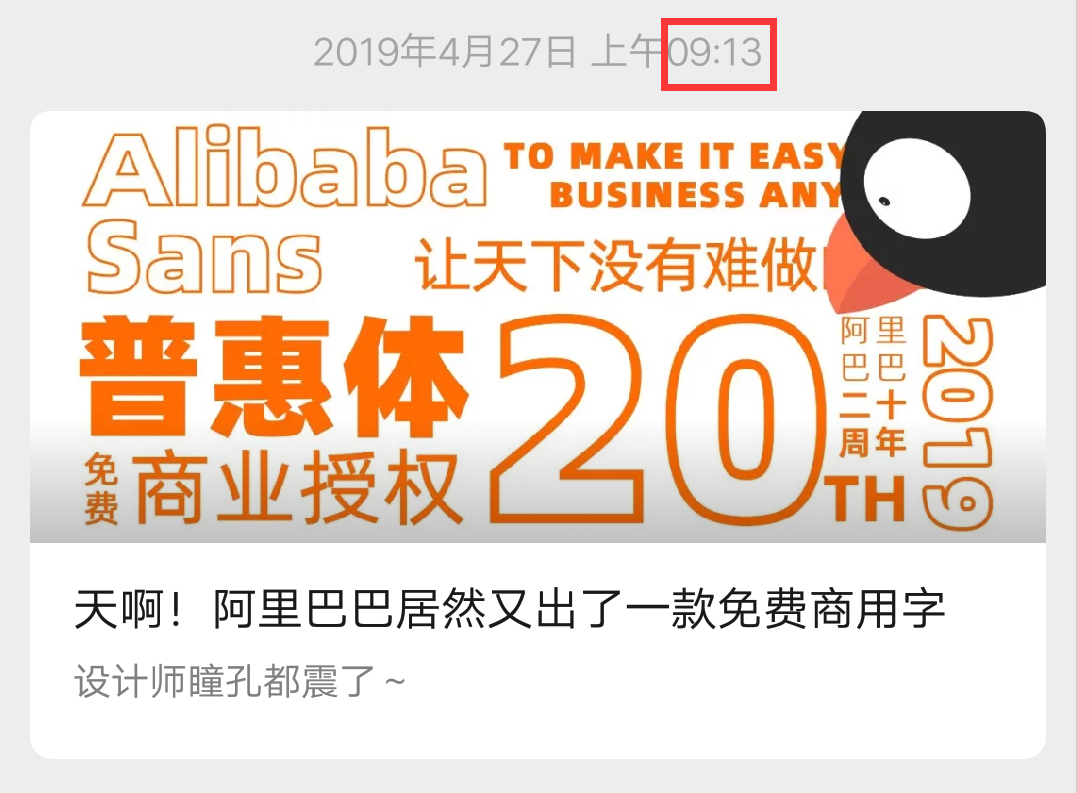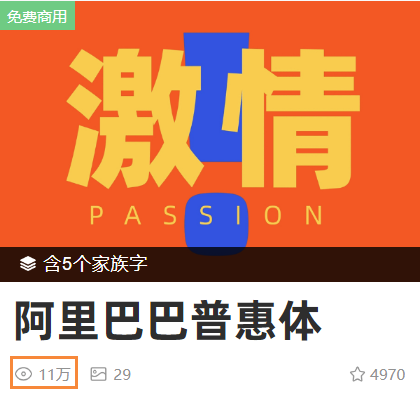
阿里巴巴普惠体2.0首发,更多字重,更多语种,永久免费!
说起阿里巴巴普惠体,不光设计师爱,跟字由的缘分也很深,因为它刚上线时,就是字由第一个发布的。
这次阿里巴巴普惠体2.0,官方和字由同步上线,让所有用户都能第一时间用上这款永久免费商用的字体(字库共囊括222841个字符,覆盖全球175个语种)。
新增4个字重
2019年发布的阿里巴巴普惠体只有5个字重,分别是bold、heavy、light、medium、regular。
这次则新增了45light、65medium、85bold、105heavy四个字重,让普惠体家族更加多元化,适用更多场景。字重名称也引入了数字,方便用户快速对九个字重进行选择和匹配。
笔画细节
普惠体2.0还完善了字体结构和细节,看起来更加清晰:比如“不”字,把撇和竖交叉的部分抹去细碎的细节,显得更加清爽;比如“原”字,处理了厂下一点与上方横线粘连的问题;比如“多”字,在斜角处做了简单的优化;比如有些字体的重心往下斜,这次也在重心上做了些微调;比如数字的设计比原来更紧凑了等。
泰语+越南语
这不普惠体2.0就新增了泰语+越南语,方便在东南亚经营的中小企业使用。
分别有regular、medium、bold三个字重,真是及时雨。
看起来阿里巴巴普惠体2.0变了,多了更多字重,更多语种,但它又没变,因为它依然是免费面向全社会,并承诺永久免费商用。